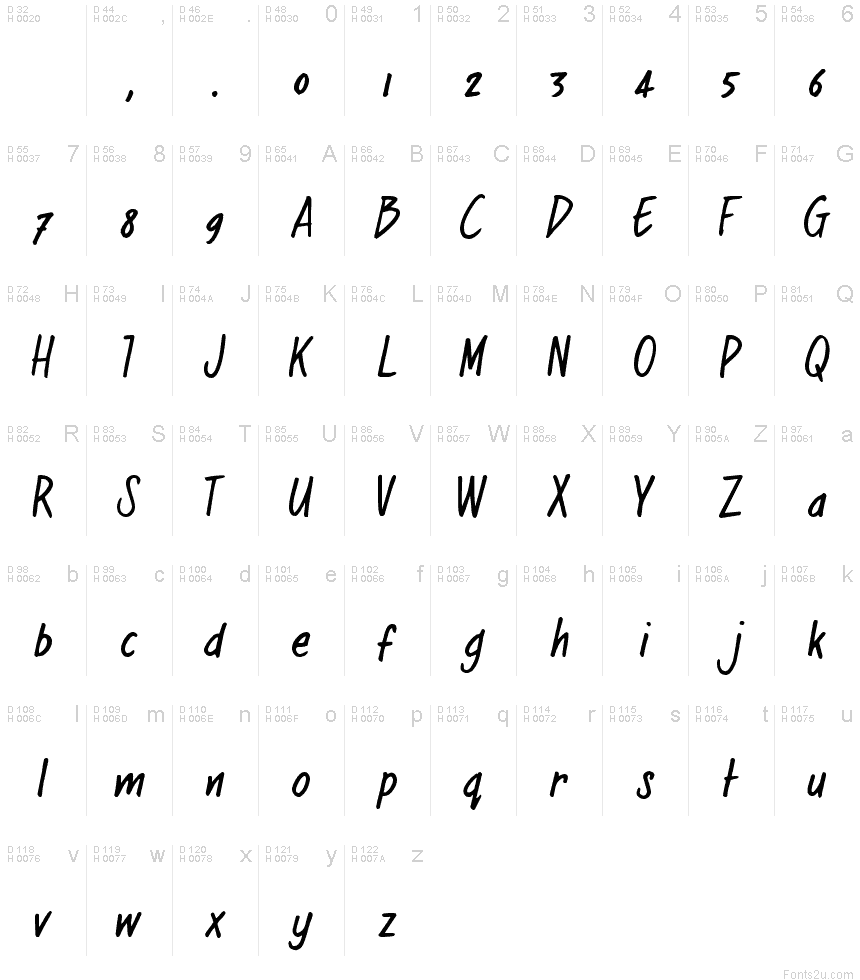
regularJoe от J O E B O B graphics — это бесплатный повседневный рукописный шрифт с непринужденным ритмом. Буквы словно нарисованы маркером: закругленные концы, мягкие соединения и легкая динамика делают длинные выносные элементы и высокие штрихи живыми и расслабленными, а не идеально выверенными.
Он органично смотрится в заголовках блогов, названиях в скрапбуках, меню кафе, заметках на упаковках и плакатах, где дружелюбный тон важнее строгого официоза. Поскольку это бесплатный шрифт, он также отлично подходит для быстрых набросков логотипов, графики для соцсетей и коротких подзаголовков, создавая легкое личное настроение без лишней вычурности.